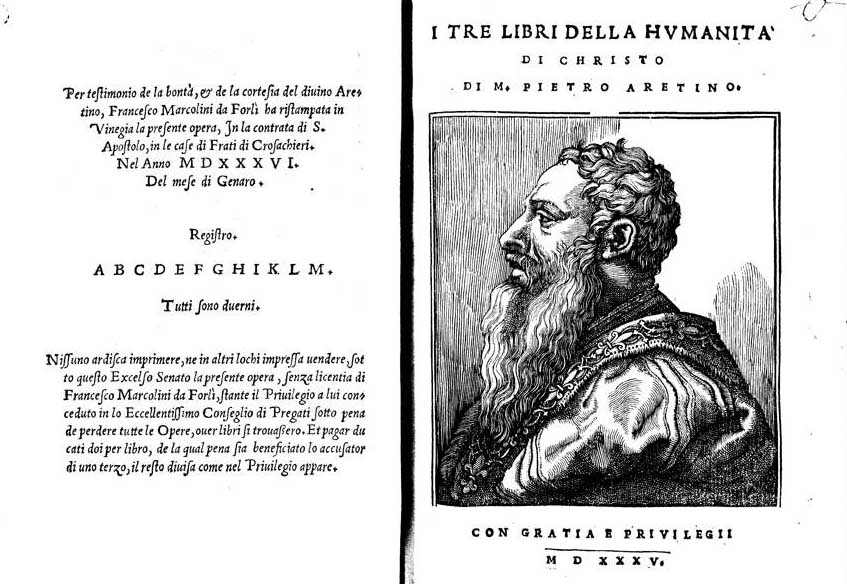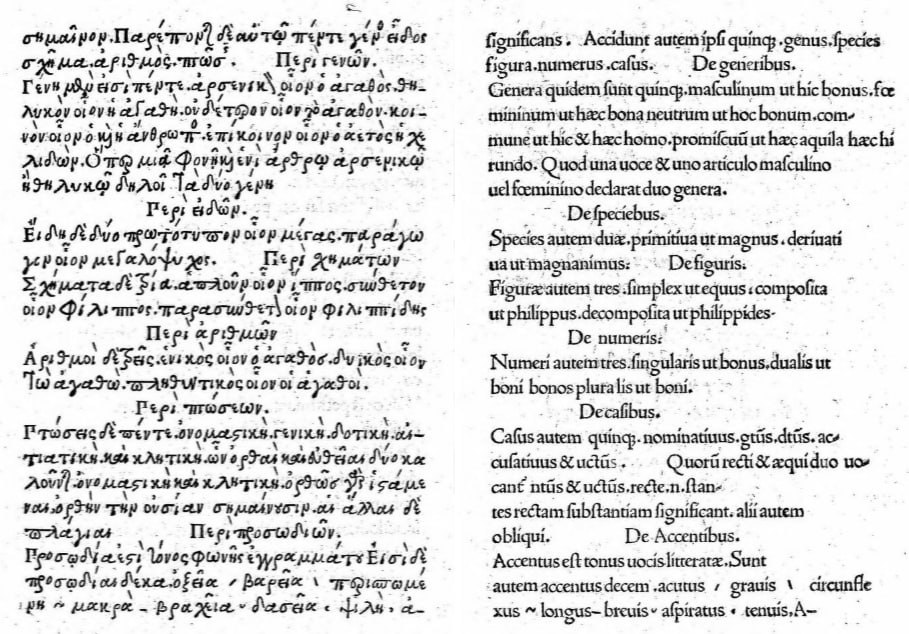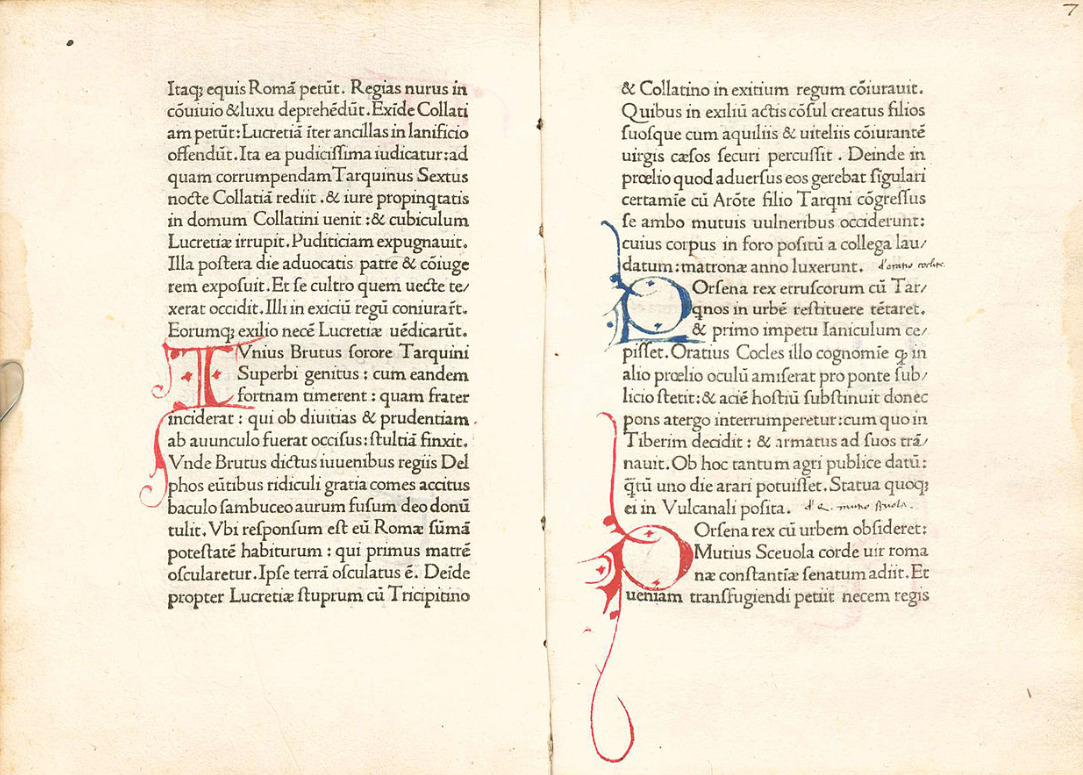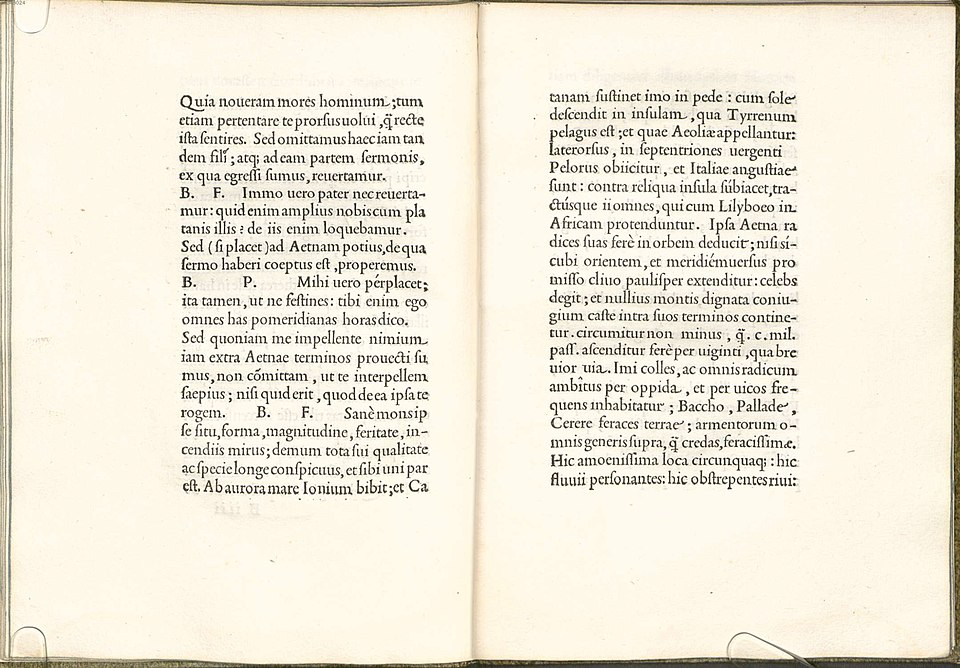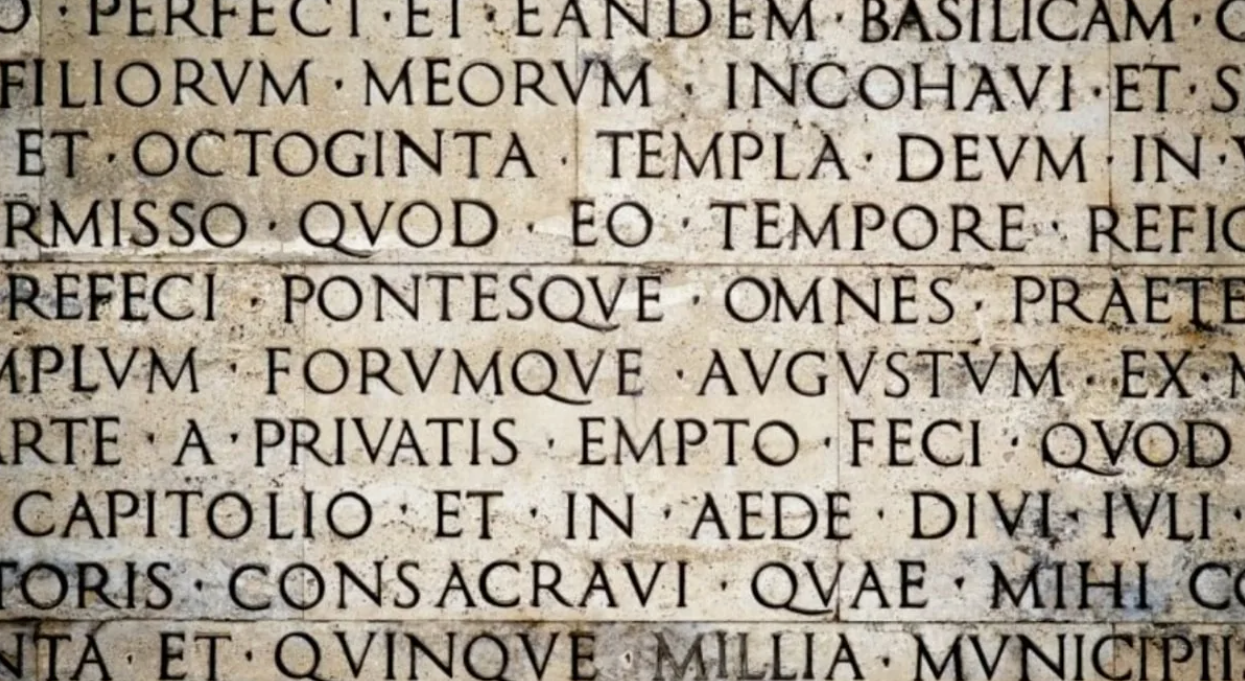
В конце предложения должна быть точка — и точка. Да, в современной сетевой переписке это уже не факт, а многими воспринимается как настаивающая и даже «токсичная» интонация, но формально правила русского и других языков с письменностями на основе кириллицы и латиницы неумолимы. Использование запятых, двое- и многоточий, дефисов и тому подобного в них тоже не слишком отличается. Более того, со второй половины XIX века европейские знаки препинания и правила их применения проникают даже в такие языки, как китайский и японский. Почему это произошло и как именно оформился привычный нам ассортимент знаков препинания? Попробуем разобраться.
В наиболее древних системах письменности, египетской иероглифике и шумеро-аккадской клинописи, изначально никаких знаков препинания не существовало в принципе: при использовании идеограмм они не слишком нужны. Современная им письменность Хараппской цивилизации долины Инда, увы, не расшифрована по сей день, и о том, что означали её знаки, мы можем лишь гадать. Со второй половины II тысячелетия до нашей эры, во времена расцвета и краха цивилизаций эпохи бронзы, в регионе Леванта на восточном берегу Средиземного моря стали появляться фонетические системы письма. Возможно, они представляли собой упрощённые формы египетской скорописи — иератического письма. Регион тогда подчинялся египетской империи Нового царства и находился под мощным влиянием египетской культуры. Однако ханаанеяне и финикийцы полностью отказались от иероглифики, резко сократили число знаков, привязав каждый из них к согласным.
Наиболее мощным выражением этого принципа стало финикийское письмо — предок множества современных систем письма, от латиницы и кириллицы через посредство греческого до иврита, арабской вязи и многочисленных индийских систем письма. Обычно в финикийском письме и его ближайших родственниках никаких знаков препинания тоже не использовалось, однако в части текстов всё же встречаются разделения слов — не пробелами (их ещё не придумали), а точками или линиями, вертикальными или косыми. И тут это уже было куда важнее, чем в египетском: поначалу гласных тут не было как класса, и при сплошной записи текстов были возможны разночтения. Финикийцы специализировались на международной морской торговле, поэтому разночтения в договорах и финансовых документах могли в буквальном смысле стоить очень дорого.
В начале I тысячелетия до нашей эры финикийское письмо заимствовали активно торговавшие и воевавшие с ними греки — они добавили в него гласные, более важные для точной записи индоевропейских языков, чем семитских вроде финикийского. Греки долгое время тоже обычно писали текст сплошным потоком без разделителей, но в ряде случаев вставляли между словами точки по центру строки, называемые в современной типографике интерпунктами. Эту практику позаимствовали римляне, у которых латинское письмо произошло от греческого через посредство этрусского к началу IV века до нашей эры. Более того, классическая латынь изначально стала, вероятно, первой системой письменности, где поначалу разделение слов интерпунктами стало стандартом.
Однако по мере того, как республика и империя расширялись, победоносные на полях сражений римляне всё больше проникались пониманием культурного превосходства греков — и образованные римляне особенно старались им подражать. Это привело к откату: раз греки обычно писали слитно, без интерпунктов, то и римляне стали всё чаще им в этом подражать в латинских текстах. Эта практика, получившая название scriptio continua, сделала чтение менее удобным и порой вызывающим непонимание: к примеру, COLLECTAMEXILIOPUBEM может быть истолкована как collectam ex Ilio pubem, что означает «народ, собранный из Трои», или collectam exilio pubem, что означает «народ, собранный для изгнания». Но, как нередко бывает, ощущение понтов было важнее удобства и рацио, и многие классические надписи на латыни римской эпохи дошли до нас именно в таком формате. Долгое время интерпункты сохранялись лишь в материалах для обучения чтению.
Впрочем, пока римляне старались уподобиться грекам даже в том, где те в действительности подотстали, греческие учёные уже задумались о дальнейших шагах, и из этих размышлений появились первые знаки препинания в строгом смысле слова — уже разделявшие не слова вместо пробелов, а смысловые группы слов. Они возникли в великой Александрийской библиотеке, где собирали, переписывали и анализировали буквально всё, что было написано к тому времени на известных грекам языках. Уже первый заведующий Александрийской библиотекой Зенодот Эфесский в III веке до нашей эры стал вводить систему пометок для анализа и коррекции ошибок при переписывании свитков. Первым придуманным им знаком стал обелюс, известный ныне как математический знак деления ÷ : он обозначал сомнительные и ошибочные, по мнению Зенодота, места в тексте. Затем появились знаки астериска, «звёздочки» ⁎ для обозначения повторяющихся в другом месте строк, полулунная сигма Ϲ и антисигма Ͻ для двух последовательных и взаимозаменяемых строк с одинаковым содержанием.
Вероятно, именно от идеи таких редакционных меток развился следующий шаг к появлению полноценных знаков препинания. Во II веке до нашей эры филолог Аристофан Византийский, заведующий Александрийской библиотекой в эпоху её расцвета, предложил ввести особую систему знаков для смысловых и дыхательных пауз разной интенсивности при чтении вслух. Точка внизу строки . , гипостигма, обозначала короткий вдох после короткой фразы — и по смыслу примерно соответствовала нашей запятой. Точка в центре строки · , стигма мезе, по сути тот же интерпункт, у него обозначала чуть более выраженную паузу и вздох подольше — это можно сравнить с нашей точкой с запятой. И, наконец, точка вверху строки ˙ , стигма телея, обозначала финал законченной мысли, «нашу» точку или даже точку в конце абзаца. Система Аристофана изначально предназначалась сугубо для помощи риторам при чтении текстов и речей вслух, и не подразумевалась для применения в других целях. Его система была воспринята теми, чья деятельность включала в себя риторику, но нередко разные люди и школы использовали разные вариации на тему, довольно популярной была более очевидная и интуитивно понятная схема с разным количеством точек: от двоеточия ⁚ и вертикального троеточия ⁝ до четырёх- ⁞ ⁘ и пятиточия ⁙ . Естественно, такая схема могла работать только при сплошном письме, scriptio continua. От аристофановых стигм со временем и произойдёт привычная нам точка, «уехавшая» в процессе вниз относительно положения своего функционального предка, стигмы телея.
Позже и там же, увы, не вполне понятно кем, были введены ещё несколько знаков, предназначенных уже не для риторов, а для читателя — чтобы избавить его от двусмысленностей при чтении сплошного потока букв. Так, появился знак гиподиастолы: небольшой полукруг ⸒ внизу строки — это возможный предок знакомой нам запятой. Он применялся при двусмысленности и сообщал, что в этом месте слова разделяются. В противоположность ему знак энотикон ‿ писался под двумя соседними буквами и показывал, что речь идёт о едином слове, если его можно воспринять как два соседних. Изобретённый Аристофаном Самосским, ещё одним заведующим Александрийской библиотеки, параграфос обозначал важное разделение в тексте между различными смысловыми блоками или репликами разных персонажей. Он не имел отношения к современному значку параграф, а представлял собой подчёркивание под несколькими буквами в начале строки, нередко с небольшим раздвоением в начале. Вероятно, параграфос произошёл от авторского значка драматурга Еврипида, который ещё в V веке до нашей эры обозначал перемену говорящего лица в пьесе положенной на бок буквой лямбда < . Вероятно, для большей однозначности Аристофан «сплющил» лямбду и поместил её под основной текст: . ⸐ . Наконец, коронис ⸎ , ромб из горизонтальных линий, обозначал конец всего текста или большого раздела.
Примерно в таком виде латинские тексты на западе и греческие на востоке пережили позднюю античность и «тёмные века», а также массовое распространение христианства, переход учёности из светских библиотек в монастыри и переход от использования свитков к книгам-кодексам привычного нам устройства. Не имело пробелов и руническое письмо, что на фоне не очень строгих орфографических правил в языке эпохи викингов ныне создаёт исследователям немало проблем. К примеру, самая длинная руническая надпись на камне из Рёка IX века содержит фрагмент ᛋᚨᚷᚹᛗᛗᛟᚷᛗᛖᚾᛁ, «sagwmmogmeni». В зависимости от границ между словами, её можно перевести как «давайте почтим память Иггдрасиля», «давайте почтим народную память» или «давайте почтим группу молодых людей».
В VII веке знаменитый энциклопедист Исидор Севильский, позже назначенный Ватиканом святым покровителем Интернета, реформировал систему Аристофана. Он оставил две точки и отвязал систему от риторики: нижняя теперь обозначала переход от одной мысли к другой внутри предложения, а средняя, интерпункт, обозначала конец предложения. Пробелы, как считается сейчас, были придуманы в Ирландии в VII-VIII веках в её монастырях, бывших в эту эпоху одними из важнейших центров почти угасшей интеллектуальной жизни Европы. Есть вполне чёткие пробелы и в знаменитой Келлской книге Евангелий, об истории создания и спасения которой рассказывает мультфильм Томма Мура «The Secret of Kells».
От монахов-ирландцев идею пробелов восприняли и их коллеги в англосаксонских королевствах. Один из них, Алкуин из Йорка, стал приближённым франкского императора Карла Великого. Он возглавил созданную в столице Каролингской империи Палатинскую академию — интеллектуальный центр Каролингского возрождения. Вместе с Алкуином из островного минускула, которым в основном пользовались ирландцы, пробелы проникли в каролингский минускул — основной шрифт Европы в последующие века до появления в XII веке готического. Однако на континенте пробелы и точки ещё долго использовались не всегда, и их применение стало более или менее стандартным лишь с XIII столетия. Более того, некоторое время использование пробелов в принципе считалось консерваторами чуть ли не варварством и дурным тоном, ибо мудрые древние писали слитно, и грамотный человек обязан и без пробелов всё хорошо понимать.
Тогда же, в XIII веке, итальянец Бонкомпаньо да Синья, преподававший в важнейших тогда университетах Болоньи и Падуи, предложил новую систему вместо аристофановско-исидоровской. У него функцию запятой выполняла косая черта / , которую да Синья назвал virgula suspensiva, а тире применялось вместо точки в конце предложения. «Длинная точка» не прижилась, а вот косая черта в качестве запятой стала использоваться в текстах достаточно регулярно. И после этого финальная точка из среднего положения благополучно «уехала» вниз на привычное нам место. Примерно в это же время возникает и знак вопроса. Изначально он был пометкой неясного места в тексте, сокращением от латинского слова quaestio, вопрос, до первой и последней букв qo. Чтобы отличать пометку от остального массива рукописного текста, их стали писать вертикально, друг над другом. А затем, со временем, q мутировала в завиток, а o в точку, и к XVI веку знак принял современную форму: ?
Окончательной систематизации системы знаков препинания в современном виде мы обязаны вполне конкретной семье венецианских книгопечатников Мандуцио, и, прежде всего, её основателю Альдо. Мы знаем, что книгопечатание с наборными литерами было создано в германских землях Иоанном Гутенбергом и его учениками и последователями. Однако германские земли того времени, за исключением нескольких торговых городов, были в основном бедными, как церковные крысы. А строительство печатных мастерских, особенно рассчитанных на солидные тиражи, было делом не просто дорогим, а очень дорогим. Состоятельные немецкие торговые дома поначалу смотрели на новую сферу с некоторым подозрением и сомнением, феодалы и монастыри — тем более, с инвесторами было туго, и первые немецкие книгопечатники сталкивались с большими финансовыми трудностями. Поэтому немецкие печатники обратили взоры на юг — в Северную Италию, на тот момент бывшую наиболее развитым в научном и культурном отношении регионом Европы. Там было куда больше и денег, и возможностей. Однако в большинстве итальянских городов интерес к книгопечатанию поначалу тоже был небольшим — даже во Флоренции, сердце Ренессанса. Говорят, увлекающиеся историей флорентийцы до сих пор злятся на своих предков, которые упустили этот шанс. Зато им великолепно воспользовалось другое государство региона.
Венецианская республика как одно из наиболее передовых и заинтересованных в инновациях государств эпохи Ренессанса очень быстро восприняла идею и потенциал книгопечатания. У этого была серьёзная экономическая основа: дело в том, что к этому времени у неё возникли очень большие проблемы с тем, что враждебная Венеции Османская империя всё больше перекрывала основу её благосостояния: торговлю товарами Востока вплоть до специй Юго-Восточной Азии через порты Восточного Средиземноморья. При этом западная часть моря была под контролем конкурента, Генуэзской республики, а океанская торговля уже плотно попала в руки португальцев и испанцев. Соответственно, доходы от морской торговли падали, и элиты республики экстренно нуждались в новых сферах вложения и приумножения капитала. Это были люди, поколениями очень хорошо разбиравшиеся в коммерции. Немалое число знатных домов Венеции уже в середине XV века увидели в книгопечатании мощный новый рынок с перспективами взрывного роста — после того, как бежавшие из разрушенного очередной войной Майнца братья Иоганн и Венделин фон Шпейер устроили в ней первую типографию в 1468 году. Как показали темпы развития книгопечатания в XVI веке, они не прогадали. Если во второй половине XV века во всей Германии работало от 10 до 15 книгопечатных заведений, а на рубеже XV и XVI веков — около 50, то в одной Венеции (!) их число к этому моменту благополучно превысило сотню. И европейский потребитель требовал ещё и ещё.
Кроме того, Serenissima Reipublicæ Venetæ имела крайне холодные отношения с римской курией, папская инквизиция на её территории была почти бессильна, и это создавало условия для печатания самой разной литературы. К примеру, во вполне католической Венеции свободно печатались протестантские библии Лютера на немецком языке для распространения в германских землях — и Suprema Congregatio Sanctæ Romanæ et Universalis Inquisitionis не могла этому помешать, хотя очень хотела. Тут же печаталась и всевозможная оккультная, алхимическая и эзотерическая литература, авторов и издателей которой в Риме хотели бы видеть исключительно на кострах из собственных книг. А в 1527 году в Венеции вышло первое в истории Европы со времён античности открыто эротическое издание — «Сладострастные сонеты» знаменитого поэта, сибарита, сатирика и тролля Пьетро Аретино. С гравюрами-иллюстрациями к оным самого откровенного характера, да ещё и за авторством знаменитого художника Джулио Романо, лучшего ученика Рафаэля Санти. При этом, говоря современным языком, спецслужбы Венеции прямо защищали скрывавшегося в городе на воде Аретино, так как за жесточайший троллинг к нему неоднократно пытались подослать убийц знатные аристократы и князья церкви, и даже несколько римских пап.
Альдо Мануцио, более известный в латинизированном варианте как Альдус Мануциус или Альд Мануций, не был урождённым венецианцем. Он родился в районе 1450 года близ Рима в патрицианской семье, получил прекрасное образование, включая латынь и греческий язык, а затем преподавал в частном порядке детям разных аристократических семейств Италии. Как и многие деятели эпохи Ренессанса, Альдо был буквально влюблён в античную культуру, и задумался о книгопечатании прежде всего для того, чтобы сделать книги древнегреческих авторов как можно более доступными. В 1490 году он с этими целями переселился в Венецию, уже ставшую главным центром европейского книгопечатания, и поначалу пытался печатать греческих авторов в уже существующих типографиях. Однако с греческими печатными шрифтами всё было довольно сложно, они имелись далеко не во всех типографиях. Зато за несколько лет Альдо оброс в Венеции немалым количеством влиятельных и состоятельных знакомых, разделявших его интересы и убеждения.
В 1494 Альдо Мануцио возглавил созданное специально для него издательство Aldino. Его основой стала типография, основанная ещё в 1470 году вторым венецианским печатником, французом Николя Жансоном. Её для Мануцио приобрели вскладчину у вдовы Жансона предприниматель Андреа Торресани и Пьетро Барбариго, племянник действующего дожа Агостино Барбариго. Эти двое, собственно, и владели предприятием в равных долях, и занимались всеми финансовыми и торговыми делами, а на Мануцио были вопросы собственно книгопечатания. Для его лучшей организации и получения толковых советов и консультаций он собрал вокруг себя круг известных тогда интеллектуалов во главе с юным. но уже прославленным деятелем эпохи Ренессанса Пьетро Бембо. Общество получило название Академия Альдина.
Первая книга нового издательства увидела свет в марте 1495 года, это был каноничный для своего времени учебник греческого языка «Эротемата» («Грамматика»). Его автором был Константин Ласкарис, грек-беженец из павшего Константинополя, знаменитый интеллектуал и знаток греческой культуры и языка. Именно он учил греческому языку и Пьетро Бембо, и многих других деятелей ренессансной Италии. За грамматикой последовало роскошное пятитомное издание Аристотеля и другие греческие тексты, древних и современных тогда авторов. При этом именно Альдо Мануцио создал книгу в том формате, который привычен нам сейчас: он ввёл практику начинать её титулом с названием, именем автора, логотипом издательства, годом и местом издания, а также нумерацию страниц, оглавления и сноски. Это было удобно и красиво, так что нововведения быстро заимствовали другие издательства Венеции и всей Европы.
Однако вскоре Альдо Мануцио, не без советов партнёров и коллег по академии, пришёл к выводу, что одними греками издательство вряд ли сможет стать рентабельным и по-настоящему популярным. Нужны книги на общепонятных в Италии языках: разных вариантах итальянского, прежде всего венецианском и тосканском, и латыни, понятной любому образованному человеку того времени. Однако встал вопрос о шрифтах. Уже братья фон Шпейер и мсье Жансон разработали и ввели в обыкновение использовать шрифты, известные как антиква и основанные на принятом тогда у образованных итальянцев рукописном «гуманистическом минускуле». Альдо Мануцио вместе со своим главным литейщиком шрифтов Франческо Гриффо создал на основе уже существовавших вариантов антиква её фирменный вариант для Aldino, отличавшийся большей компактностью.
Однако это было не всё: если в «Эротемате» латинские страницы ещё имели довольно сумбурную пунктуацию, то теперь Мануцио решил сделать её в своих изданиях чёткой и систематизированной. Таким образом в антикве Альдина появились вполне современно выглядящие знаки пунктуации: точки, запятые, точки с запятой, двоеточия, тире при переносе слов на следующую строку и заменявшие союз «и» лигатуры &. Именно в этот момент Альдо сделал запятую в современном виде , вместо введённой да Синья косой черты / — вполне вероятно, в силу любви к греческому языку и книгам древнегреческих авторов, он взял на эту позицию слегка изменённый знак гиподиастолы ⸒ . Для смысловой паузы, большей, чем выражаемой запятой, но меньшей, чем конец предложения, он ввёл знак точки с запятой ; . Тут же возникает и двоеточие для выражения пояснения. Более того, Мануцио дополнил уже существовавший знак вопроса ? и дополнил его восклицательным знаком ! , о чём можно привести его цитату из трактата Institutionum Grammaticarum Libri Quatuor:
Поскольку в конце предложения может быть или вопрос, или какое-то чувство, например, негодование, восхищение, сострадание, мы покажем это разными сигналами: точкой рядом с последней буквой с наложенной витой чертой в случае вопроса и прямой чертой в случае чувства.
При этом для большей эстетической схожести с рукописным текстом в наборах буквы и знаки препинания имели по несколько слегка различавшихся вариантов. Со знаками препинания был особенный разнобой, возможно, Мануцио и сам не был уверен, как именно лучше их ставить: посредине между буквами с пробелами или без пробелов, у предыдущей или у последующей. В его изданиях встречались разные варианты на одной и той же странице. Возможно, свою роль играло и то, что требовалось выравнивать текст строго по обеим сторонам колонки, и для этого могло требоваться разное количество дополнительных или изъятых пробелов.
Первой книгой, изданной Альдо Мануцио сугубо на латыни, стал диалог Пьетро Бембо De Aetna ad Angelum Chabrielem liber. Он был написан под впечатлением от времени, проведённого в сицилийской Мессине, где Бембо учился греческому языку у Константина Ласкариса, и особенно о восхождении на знаменитый вулкан Этна с приятелем Анджело Габриэле. Правда, до вершины им добраться не удалось: вулкан внезапно стал проявлять активность, и друзья сочли за лучшее поскорее убраться с его склонов. Впрочем, большая часть книги, выполненной в форме рассказа Пьетро о путешествии к отцу, представляет собой не путевые заметки, а попутные рассуждения об античной истории, литературе и современной автору политической жизни.
Книга Бембо была напечатана в 1496 году новым фирменным шрифтом со всеми систематизированными Мануцио знаками препинания, который в честь автора и друга издателя получил название Bembo. Считается, что тем она открыла новую эпоху в книгопечатании. С 1505 года Мануцио по совету всё того же Пьетро Бембо начинает массовую печать книг в формате, ранее почти не принятом: in octavo, в восьмую часть тогдашнего типографского листа, что примерно соответствует обычному ныне размеру книги. De Aetna была напечатана в формате in quarto, большем современного листа А4. In octavo — между А4 и А5. Их можно было легко носить с собой или перевозить, они проще помещались на полках, и они были значительно дешевле более традиционных и крупных форматов. Чтобы сделать книги компактнее и в ширину, Мануцио и Гриффо в 1501 году изобрели на основе Bembo курсивный шрифт, позволявший укладывать строки и буквы более компактно при сохранении читаемости. В силу итальянского происхождения в английском языке курсив по сей день называется italic.
Впрочем, Мануцио всегда старался делать книги с упором на качество, а не доступность, и стоили его ин кватро всё же солидно, но в Венеции и Италии в целом хватало платёжеспособных ценителей книг. И ин кватро, и вообще издания Альдо получили огромную популярность — у библиофилов за ними закрепилось специальное название: «альдины». Он успел выпустить 143 разных изданий на латыни, греческом и итальянском, и некоторые из них, к примеру, сборник сонетов Петрарки в формате ин кватро, разошлись колоссальными тиражами даже по современным временам, более 100 тысяч экземпляров. Сам Мануцио умер в 1515 году, успев разругаться с Гриффо на почве авторских прав на шрифты, но его дело унаследовали сын Паоло, а затем внук Альдо Мануцио-младший, попутно ставший крупным теоретиком и систематизатором итальянской грамматики, и окончательно закрепивший введённые дедом знаки препинания. Издательство Aldino большую часть XVI века было одним из ведущих в мире, а его символ — предложенный Бембо обвивающий якорь дельфин — был признанным знаком качества. Увы, но дети Альдо Мануция-младшего после его смерти в 1597 году предпочли заняться другими делами, и издательство прекратило своё существование.
Результатом этого было то, что они стали законодателями мод в книжной индустрии — и остальные ориентировались на них. Именно поэтому пунктуационная система Альдо Мануцио к концу XVI века стала общеитальянским стандартом, а в XVII веке и общемировым. Первые книжные издания Шекспира в Англии 1623 года уже использовали именно его подход к знакам препинания. После петровских реформ и введения гражданского шрифта он перекочевал и в русское книгопечатание. И в таком виде, с некоторыми дополнениями и различиями в разных языках, эта система знаков пунктуации сохраняется и по сей день в большинстве языков.